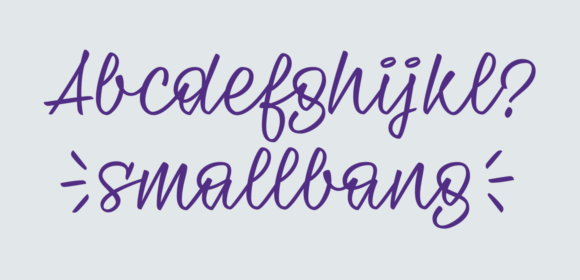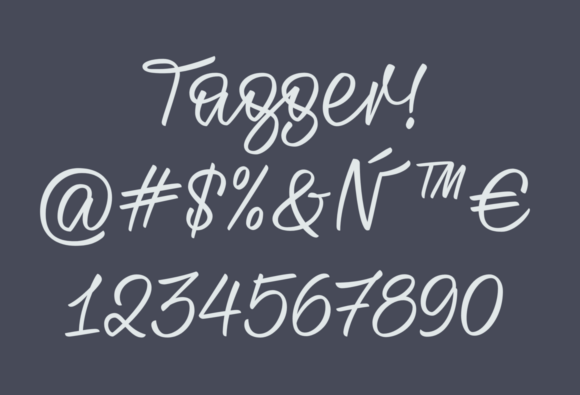
Tagger: Free Calligraphy Font Inspired to Graffiti Tags
Tagger: Free Kalligraphie Font für Graffiti Tags
Tagger ist eine kostenlose Kalligrafie-Schriftart, entworfen von Zuzanna Rogatty, einer Designerin, Kalligrafin und Art Directorin mit Sitz in New York.
Die Schriftart Tagger wurde von den Graffiti-Tags inspiriert, die in Warschau zu finden sind, und zeigt dynamische Zeichen und informelle Formen. Perfekt zur Festlegung der visuellen Identität von Bars, Restaurants und Geschäften ist Tagger vielseitig genug, um in Speisekarten, Preisschildern, Etiketten und verschiedenen anderen Anwendungen eingesetzt zu werden.